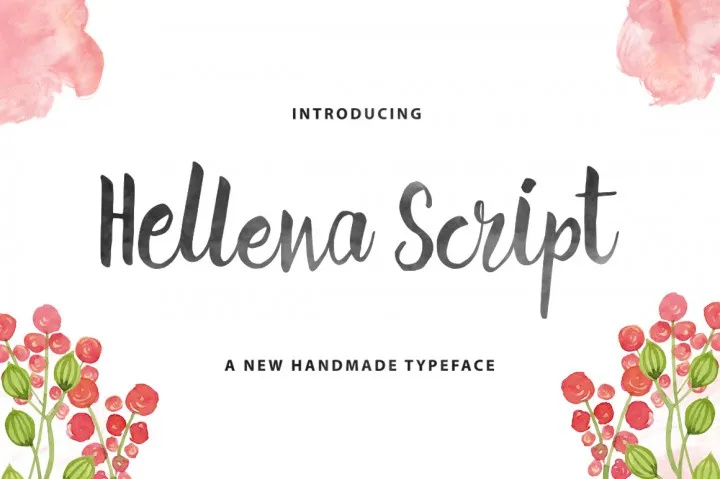
A fonte Hellena Script é uma opção ideal para designers que procuram a elegância das fóruns manuscritas combinada com a sofisticação premium. Desenvolvida pelo designer 178-MC, essa fonte traz um estilo cuidadosamente elaborado, perfeito para criar design gráfico impecável. Hellena Script é uma fonte handwritten que oferece nuances de personalidade e expressividade, tornando-a uma escolha favorita entre os designers. Esta é especialmente útil em projetos onde se espera transmitir um tom delicado ou uma atmosfera sofisticada, como no design de logotipos, letras grandes para outdoors ou até mesmo na criação de capas de livros. Para as pessoas que buscam essa fonte premium com desconto temporário (somente disponível por 7 dias), Hellena Script pode ser a escolha ideal. O designer 178-MC manteve o alto padrão de qualidade e estilo da font, oferecendo uma experiência gratificante para os designers no período limitado. Não perca esta oportunidade única, pois essa font é rara em seu tipo de personalização e refinamento.